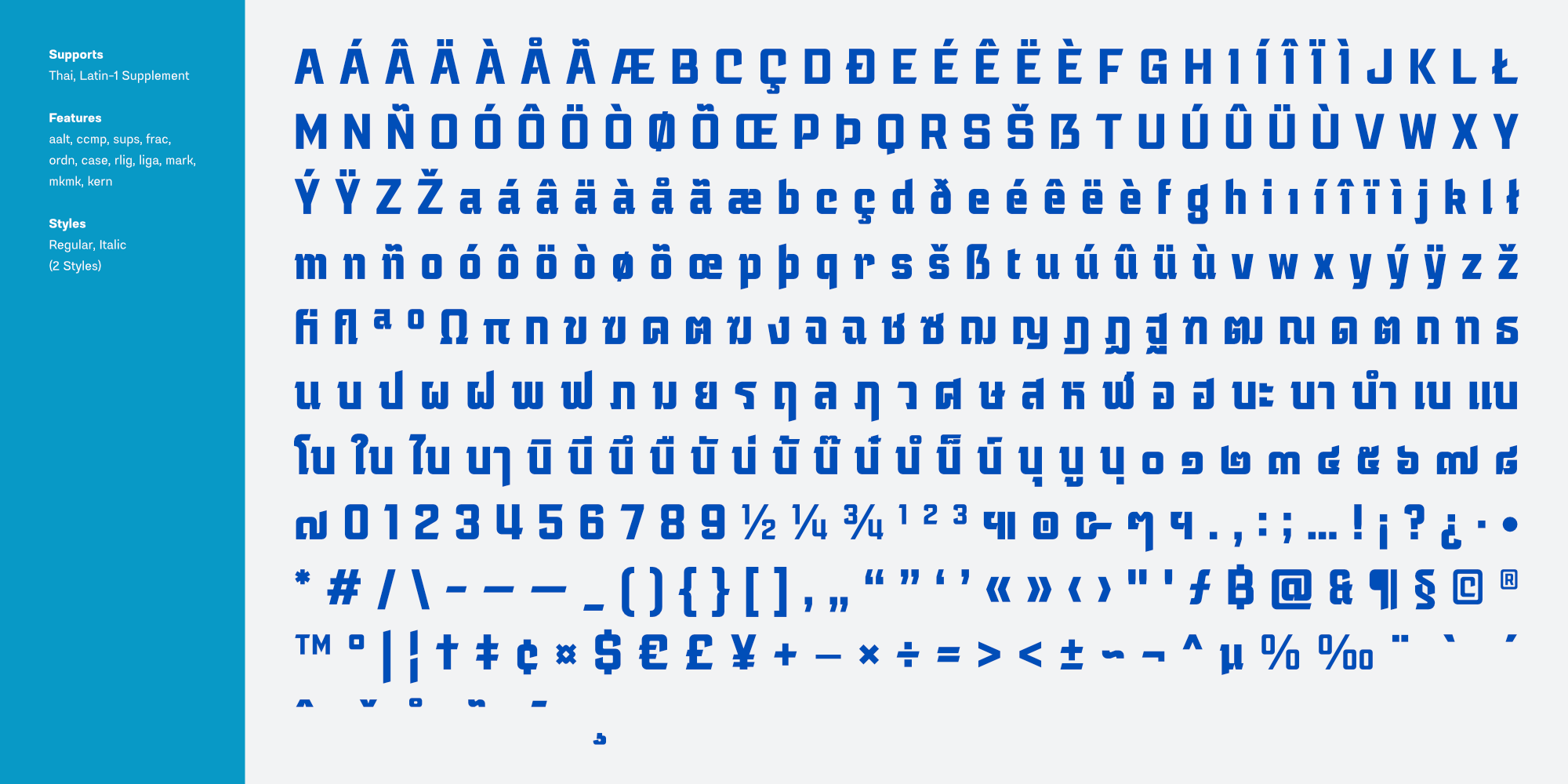
ยนตรกรรม | Yontrakam
ชื่อฟอนต์ : ยนตรกรรม | Yontrakam
ยนตรกรรม เป็นอักษรแบบพาดหัว มีรูปลักษณ์ที่ตัวหนและคมเข้ม ให้ความรู้โฉบเฉี่ยว อนาคตนิยม และไซไฟ เหมาะสำหรับการนำไปใช้ผาดหัวบนสื่อต่างๆ หรือข้อความที่ต้องการเน้นความสำคัญเป็นพิเศษ เช่น โปสเตอร์ แพคเกจจิ้ง และอื่นๆ อีกมากมาย